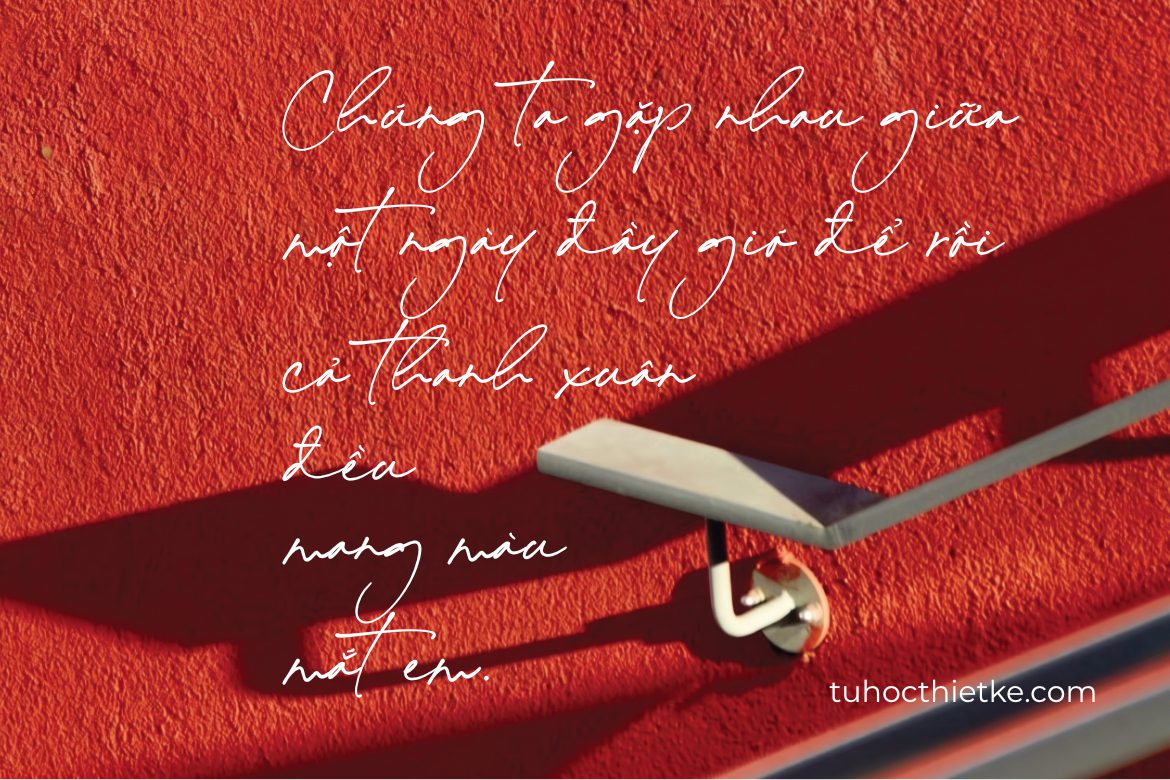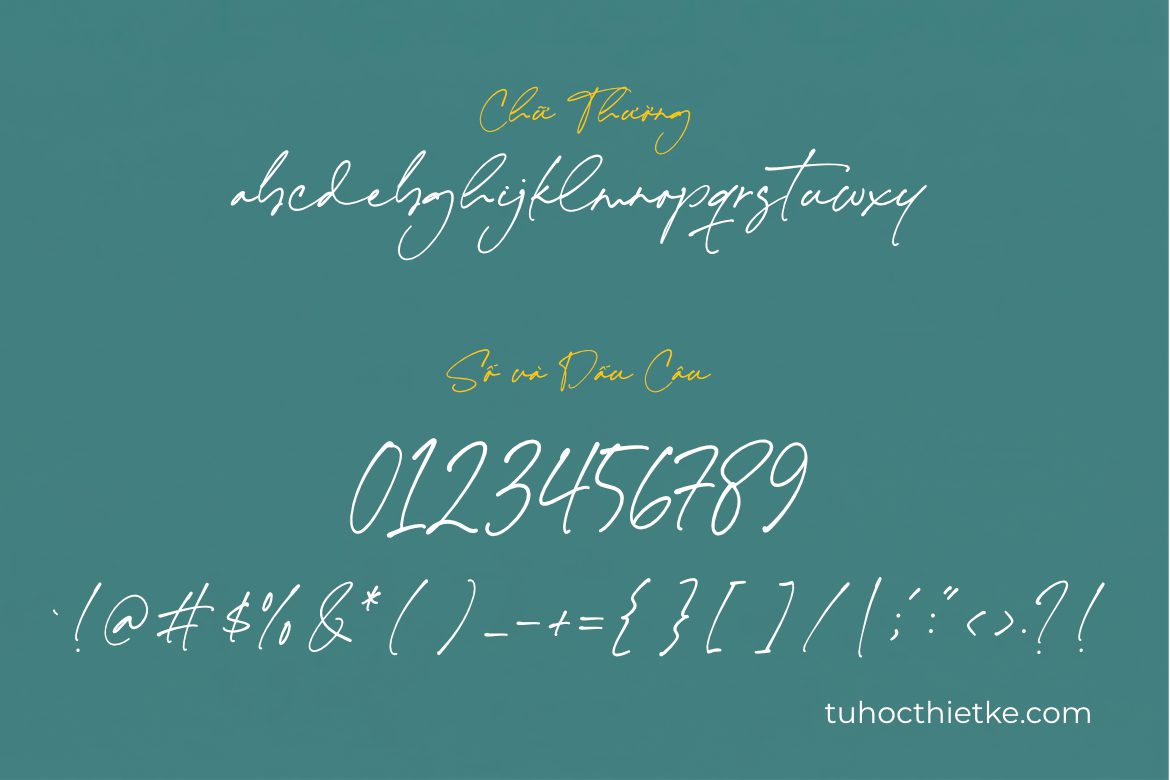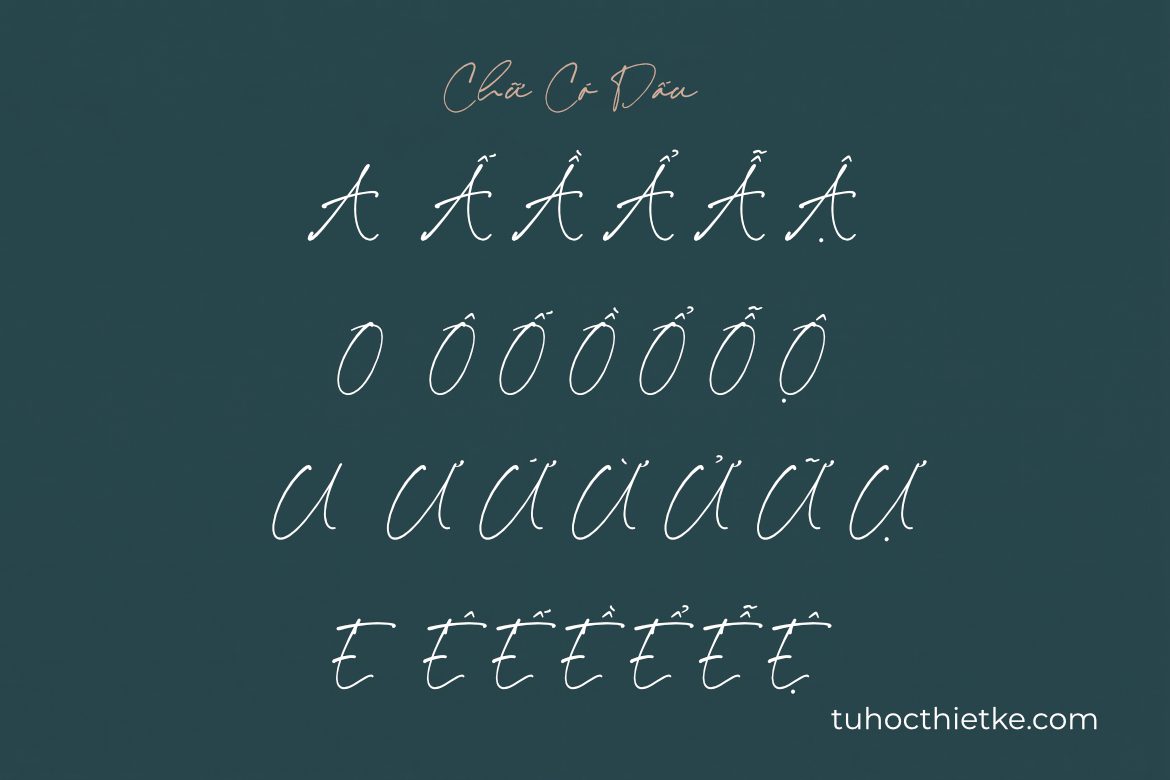
Trong thiết kế đồ họa, font chữ là một trong những yếu tố quan trọng giúp truyền tải cảm xúc, phong cách và cá tính của thương hiệu. Một mẫu font phù hợp có thể biến một thiết kế đơn giản trở nên sang trọng, tinh tế và chuyên nghiệp hơn. Trong số các dòng font được nhiều designer yêu thích, font chữ viết tay luôn có sức hút đặc biệt nhờ vẻ mềm mại, tự nhiên và gần gũi. Nếu bạn đang tìm kiếm một mẫu Font Chữ Việt Hóa mang phong cách chữ ký thanh lịch, Woodsen Signature chắc chắn là lựa chọn đáng để trải nghiệm.
Woodsen Signature là kiểu font viết tay có đường nét uyển chuyển, mềm mại và giàu tính nghệ thuật. Font mang cảm giác giống như chữ ký cá nhân, phù hợp với các thiết kế cần sự tinh tế, sang trọng và mang dấu ấn riêng. Với phiên bản được Việt hóa, Woodsen Signature có thể hiển thị tốt tiếng Việt, giúp designer dễ dàng ứng dụng vào nhiều dự án thực tế mà không lo lỗi dấu hay thiếu ký tự.
Font Woodsen Signature Là Gì?
Woodsen Signature là mẫu font thuộc phong cách handwritten hoặc signature font, tức là kiểu chữ mô phỏng nét viết tay và chữ ký tự nhiên. Font thường có các đường cong mềm, nét nối uyển chuyển và dáng chữ thanh thoát. Đây là lựa chọn lý tưởng cho những thiết kế cần cảm giác cá nhân hóa, nhẹ nhàng nhưng vẫn cao cấp.
Đặc Điểm Nổi Bật Của Woodsen Signature
Điểm nổi bật nhất của Woodsen Signature nằm ở nét chữ bay bổng, có độ nghiêng nhẹ và mang cảm giác thủ công. Các ký tự được thiết kế không quá cứng nhắc, tạo nên sự tự nhiên giống như được viết bằng bút thật. Nhờ đó, font có thể tạo điểm nhấn rất tốt cho tiêu đề, logo, chữ ký thương hiệu, thiệp mời hoặc các ấn phẩm mang phong cách nghệ thuật.
So với nhiều font viết tay khác, Woodsen Signature có ưu điểm là vừa mềm mại vừa dễ đọc. Đây là yếu tố quan trọng, bởi một số font chữ ký thường quá cầu kỳ, khiến người xem khó nhận diện nội dung. Woodsen Signature giữ được sự cân bằng giữa tính thẩm mỹ và khả năng ứng dụng.
Vì Sao Nên Dùng Font Woodsen Signature Việt Hóa?
Khi làm thiết kế bằng tiếng Việt, việc chọn font hỗ trợ đầy đủ dấu là điều rất cần thiết. Một font đẹp nhưng không Việt hóa có thể làm chữ bị lỗi, lệch dấu hoặc hiển thị không đồng đều. Điều này ảnh hưởng trực tiếp đến chất lượng thiết kế, đặc biệt là các sản phẩm cần sự chỉn chu như logo, poster, banner quảng cáo hay ấn phẩm thương hiệu.
Hỗ Trợ Tiếng Việt Đầy Đủ
Phiên bản Font Chữ Việt Hóa Woodsen Signature giúp hiển thị tốt các ký tự tiếng Việt như ă, â, ê, ô, ơ, ư, đ cùng các dấu sắc, huyền, hỏi, ngã, nặng. Nhờ đó, bạn có thể sử dụng font cho tiêu đề, slogan, tên thương hiệu hoặc nội dung ngắn bằng tiếng Việt một cách thuận tiện.
Việc sử dụng font đã Việt hóa giúp tiết kiệm thời gian chỉnh sửa, tránh tình trạng phải thay font khác khi gặp lỗi dấu. Đây là lợi thế lớn đối với designer thường xuyên làm việc với khách hàng Việt Nam hoặc các dự án nội dung tiếng Việt.
Mang Lại Cảm Giác Sang Trọng Và Cá Nhân Hóa
Woodsen Signature không chỉ đẹp ở hình thức mà còn mang lại cảm giác rất riêng cho thiết kế. Những đường nét giống chữ ký giúp sản phẩm trông cá nhân hóa hơn, phù hợp với các thương hiệu muốn thể hiện sự tinh tế, thủ công, nhẹ nhàng hoặc cao cấp.
Font đặc biệt phù hợp với các lĩnh vực như thời trang, mỹ phẩm, studio ảnh cưới, spa, tiệm bánh, handmade, florist, boutique hoặc thương hiệu cá nhân. Khi được sử dụng đúng cách, Woodsen Signature có thể giúp tổng thể thiết kế trở nên cuốn hút và dễ ghi nhớ hơn.
Ứng Dụng Của Font Woodsen Signature Trong Thiết Kế
Một mẫu font đẹp cần có khả năng ứng dụng linh hoạt trong nhiều bối cảnh khác nhau. Woodsen Signature là kiểu font có thể dùng cho cả thiết kế in ấn lẫn thiết kế kỹ thuật số, từ các dự án cá nhân đến sản phẩm thương mại.
Thiết Kế Logo Và Nhận Diện Thương Hiệu
Woodsen Signature rất phù hợp để thiết kế logo dạng chữ ký, đặc biệt là các thương hiệu muốn tạo cảm giác mềm mại và cao cấp. Bạn có thể dùng font cho tên thương hiệu chính, sau đó kết hợp với một font phụ đơn giản để làm tagline hoặc mô tả ngành nghề.
Ví dụ, một logo tiệm bánh, studio ảnh, shop thời trang nữ hoặc thương hiệu mỹ phẩm handmade sẽ trở nên tinh tế hơn khi dùng Woodsen Signature làm điểm nhấn. Nét chữ tự nhiên giúp logo có cảm giác gần gũi nhưng vẫn chuyên nghiệp.
Thiết Kế Thiệp Cưới, Thiệp Mời Và Sự Kiện
Với phong cách chữ viết tay lãng mạn, Woodsen Signature là lựa chọn lý tưởng cho thiệp cưới, thiệp sinh nhật, thiệp cảm ơn, menu tiệc, bảng welcome hoặc các ấn phẩm sự kiện. Khi kết hợp với màu pastel, nền giấy mỹ thuật, họa tiết hoa lá hoặc texture vintage, font sẽ tạo nên cảm giác nhẹ nhàng và trang nhã.
Đối với các thiết kế cưới, bạn có thể dùng Woodsen Signature cho tên cô dâu chú rể, tiêu đề chính hoặc các câu quote ngắn. Điều này giúp ấn phẩm trở nên mềm mại, cảm xúc và có dấu ấn riêng hơn.
Thiết Kế Ảnh Quote, Poster Và Social Media
Trong thiết kế mạng xã hội, font chữ đẹp giúp nội dung nổi bật và dễ thu hút người xem hơn. Woodsen Signature có thể dùng để tạo ảnh quote, poster truyền cảm hứng, banner khuyến mãi, ảnh bìa Facebook, thumbnail hoặc bài đăng Instagram.
Nếu bạn đang tìm kiếm một mẫu Font Chữ Việt Hóa phong cách chữ ký để bổ sung vào bộ sưu tập thiết kế, Woodsen Signature là lựa chọn đáng cân nhắc. Với đường nét uyển chuyển, khả năng hiển thị tiếng Việt tốt và tính ứng dụng cao, font này sẽ giúp bạn dễ dàng tạo ra những thiết kế tinh tế, tự nhiên và cuốn hút hơn.